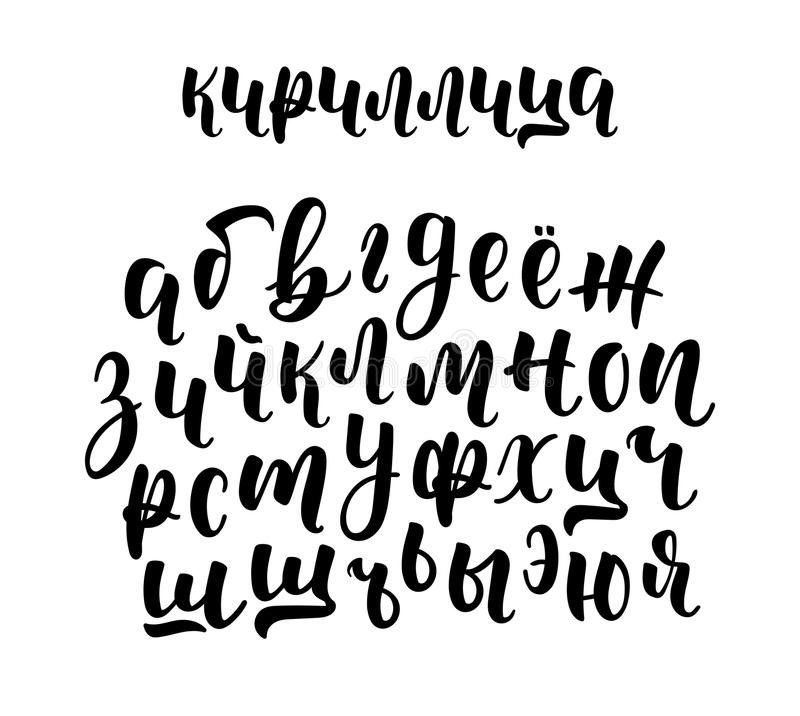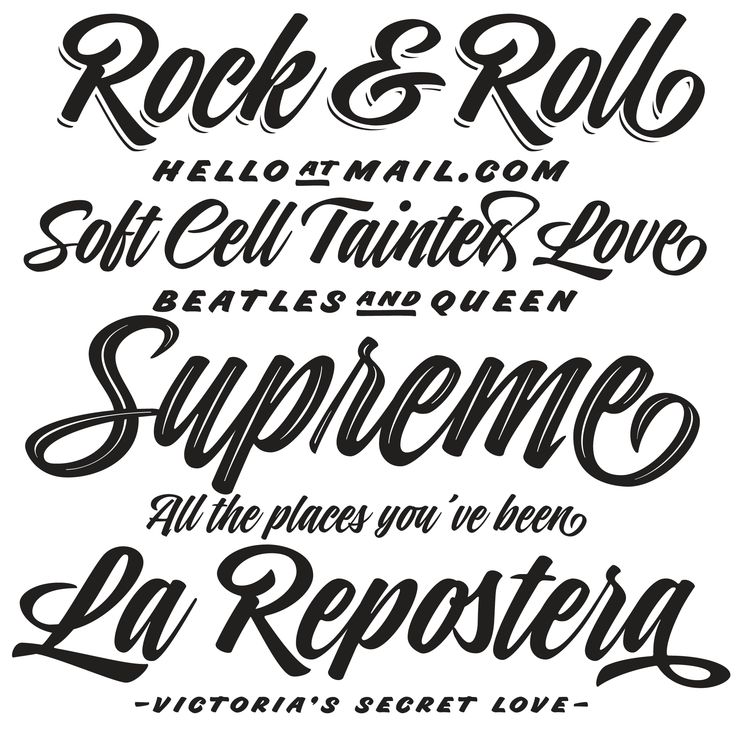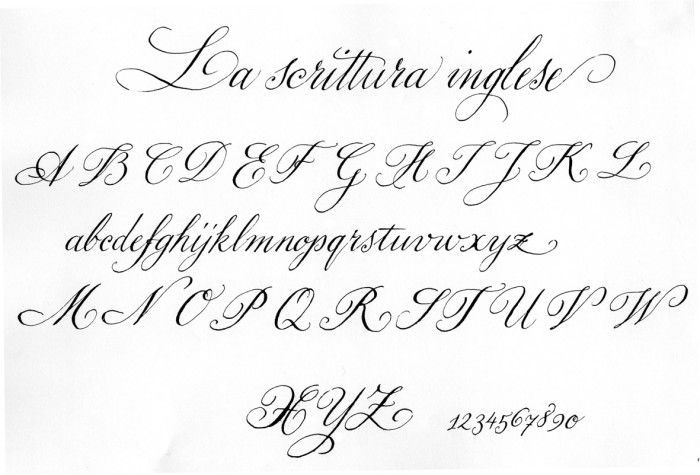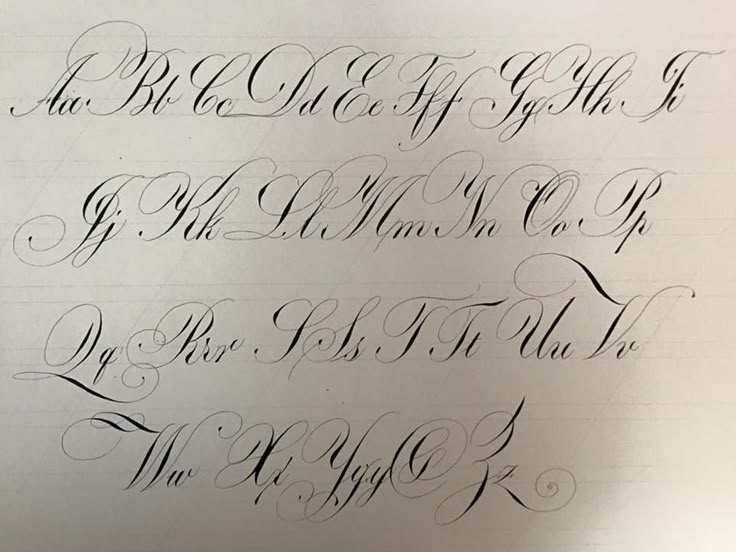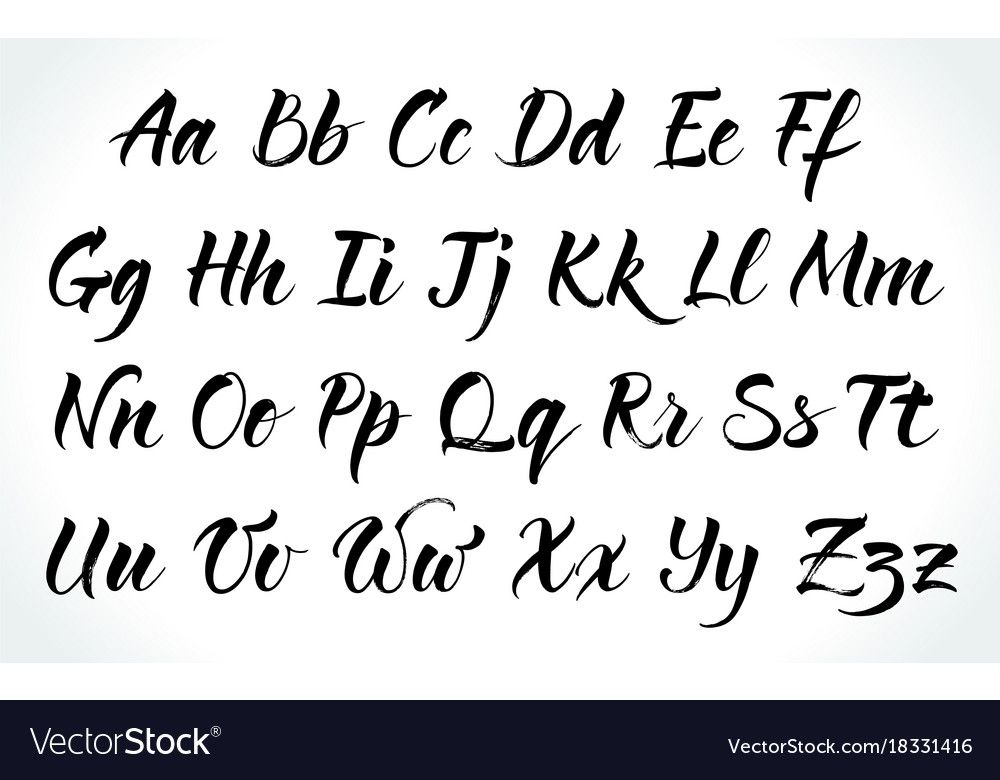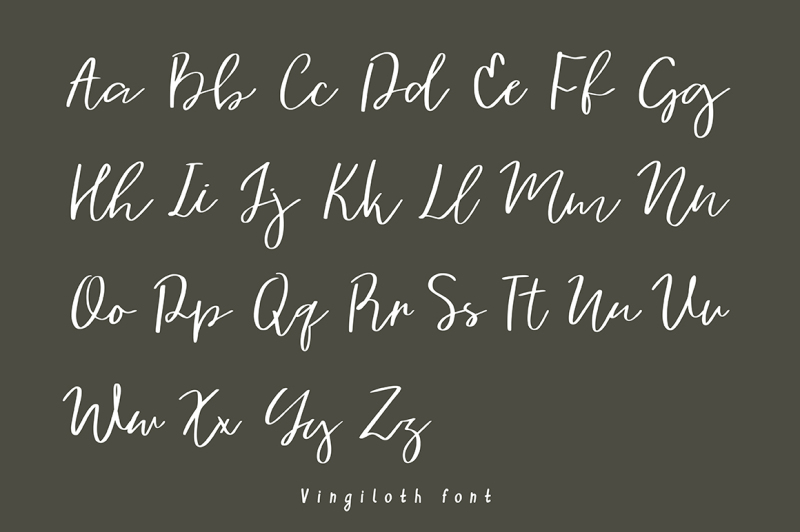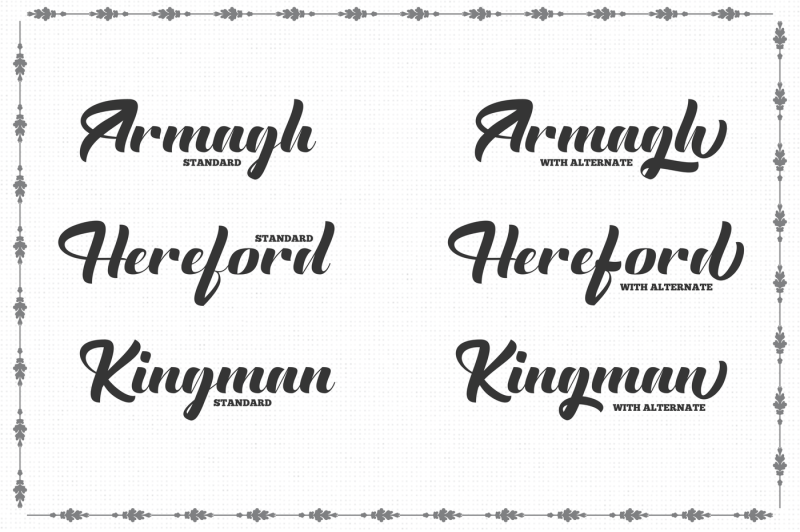
40 лучших бесплатных рукописных шрифтов для дизайнеров в 2020 году
Рукописные шрифты — это простой способ добавить индивидуальности вашему контенту.
Дизайнеры используют их для создания привлекательных логотипов и цитат на веб-сайтах, потому что они резко контрастируют с основным текстом. Хотя рукописные шрифты не особенно подходят для корпоративного контекста или профессиональных документов, они являются отличным выбором для личных блогов, веб-сайтов, посвященных искусству и ремеслам, комиксов, ресторанных меню и рекламы, а также для малого бизнеса в творческой индустрии. Рукописные шрифты особенно популярны благодаря тенденции в веб-дизайне к леттерингу, потому что эффект рукописного письма может быть достигнут с помощью декоративных шрифтов. Вы даже можете создавать свои собственные рукописные шрифты бесплатно!
Лучшие бесплатные рукописные шрифты для дизайнеров в 2020 году
В этом списке представлены 40 рукописных шрифтов, которые бесплатны для коммерческого использования. Хотя они не все новые, это проверенные рукописные шрифты, которые нам нравятся. Репозитории шрифтов классифицируют рукописные шрифты по-разному, поэтому некоторые из них могут быть помечены как «сценарные», «каллиграфические» или «декоративные» в зависимости от веб-сайта.
40. Сценарий покупок
Для впечатляющего рукописного письма в стиле курсивной подписи «Сценарий покупок» кажется прекрасным вариантом. Это довольно простой, но красивый шрифт, и, что более важно, он обладает качеством, позволяющим вашей подписи оставить неизгладимое впечатление.